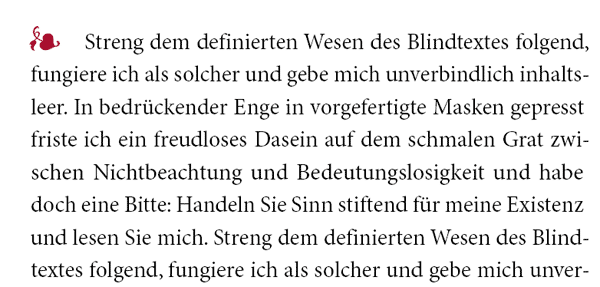
Aldusblatt als Initial?
Das geht schon, ich stimme allerdings Norbert zu, daß ein Symbol mit einem Bezug besser wäre. Ich habe das mal in einem Weinbuch mit einer stilisierten Rebe gesehen und fand das sehr ansprechend.
Geht das übrigens nur mir so? In der gezeigten Version erscheint es mir, als ob das Alsdus-Blatt nicht so recht etwas mit dem Text zu tun haben möchte. Das würde mich persönlich in jedem Fall am meisten stören. Der Abstand wäre mir zu groß, es ragt minimal zu weit nach links und auch zu weit nach oben. Die Kombination vom dunklen Text mit dem rot gefällt mir hingegen wiederum sehr gut, gerade auch für den Bereich Gastronomie. Die stilisierte Rebe war in einem kräftigen grün, welches leicht ins blau ging, was (gerade im Zusammenhang »Wein«) auch sehr gut mit dunklem Text aussah.
In der gezeigten Version erscheint es mir, als ob das Alsdus-Blatt nicht so recht etwas mit dem Text zu tun haben möchte. Das würde mich persönlich in jedem Fall am meisten stören. Der Abstand wäre mir zu groß, es ragt minimal zu weit nach links und auch zu weit nach oben.
Genau das hat mich auch gestört.
Ich seh ja auch in so einem Symbol eine Mittel- und Oberlänge. Wahrscheinlich hilft es schon, sich an den Maßen der Schrift zu orientieren: "Blatt" auf Minuskelhöhe, "Grünzeug" auf Oberlänge. Einen Versuch wert.
Und:
Höchstens zu jedem Kapitelanfang, nicht Absatzanfang.
Eventuell tatsächlich zum jeweiligen Thema passend wechselnd.
Abseits davon: Der Doppeltpunkt hinter "Bitte" braucht noch etwas Luft, der klebt so am "e" dran.
Mit der Position und Größe des Symbols habt ihr Recht. War auch nur auf die schnelle gemacht, zur Ansicht.
Das mit den wechselnden Initialen gefällt mir sehr gut. Super wäre es natürlich Initiale zu haben die zum Gericht auf der Vorderseite passen. Mal schauen ob ich etwas geeignetes finde. Bei den Texten geht es um jeweils einseitige Restaurantbeschreibungen auf den Rückseiten eines Kalenders. Ich werde die Initiale nur am Textanfang setzen, daher werden die sich nicht oft wiederholen.
Wenn es ein Monatskalender ist, wären es doch eh nur 12 Motive. Entwirf da doch lieber selbst was ...